Pahlawan Tegar
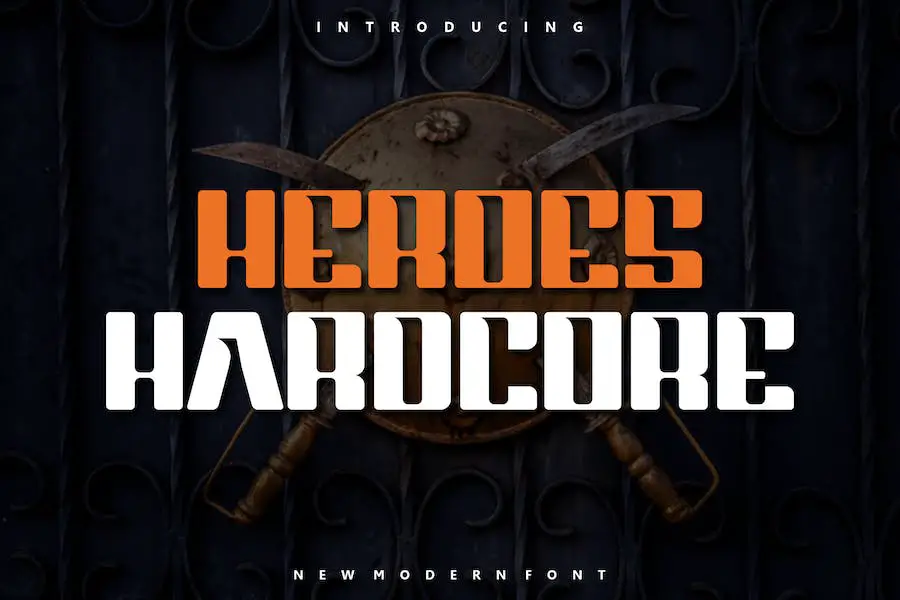
Heroes Hardcore adalah font luar biasa yang menghadirkan sentuhan berani dan autentik pada proyek desain Anda. Baik Anda sedang mengerjakan logo, pencetakan kaos, atau bahkan desain esport, font modern ini sangat cocok untuk menambahkan elemen yang kuat dan berdampak.
Dengan keserbagunaan dan gayanya yang unik, Heroes Hardcore menonjol dalam berbagai konteks dan akan meningkatkan keseluruhan tampilan dan nuansa kreasi Anda.
Kekuatan Heroes Hardcore terletak pada keberanian dan keasliannya. Font ini memancarkan kepercayaan diri dan memberikan kesan kuat dalam desain apa pun. Garis-garisnya yang bersih dan tepinya yang tajam memberikan tampilan yang modern dan ramping, dengan tetap mempertahankan sentuhan keunikan.
Saat digunakan dalam proyek branding, Heroes Hardcore menambahkan kepribadian dan karakter, membuat merek Anda menonjol dari pesaing.
Kasar
Hardcore adalah font unik yang menghadirkan sentuhan urban segar pada desain Anda. Skrip penuh gaya ini sempurna untuk menambahkan daya tarik yang menarik pada logo, citra merek, kutipan, kemasan produk, barang dagangan, dan postingan media sosial Anda.
Dengan estetikanya yang edgy dan modern, Hardcore adalah pilihan utama bagi para desainer yang ingin tampil berani. Baik Anda membuat logo untuk merek mutakhir atau mendesain grafis media sosial yang menarik perhatian, font ini siap membantu Anda.
Keserbagunaan dan nuansa trendinya menjadikannya suatu keharusan bagi setiap desainer yang ingin membawa proyek mereka ke tingkat berikutnya.
Distem
Distem adalah font logo hardcore yang menonjolkan gaya Horror Metal yang unik dan sangat detail. Sempurna untuk menambahkan sentuhan keren pada desain Anda, ini adalah pilihan yang sangat baik untuk desain retro-urban, branding untuk bisnis tato, logo, desain vintage, dan banyak lagi.
Estetikanya yang berbeda membedakannya dan menjadikannya font yang bagus untuk menciptakan visual yang menarik. Dengan tingkat detailnya yang mengesankan, Distem pasti akan memberikan kesan abadi dan menambahkan sentuhan kegelapan pada proyek Anda.
Baik Anda sedang mengerjakan logo, branding, atau proyek desain lainnya, font ini layak dipertimbangkan karena keserbagunaan dan dampaknya yang berani.
Hipster garis keras
Hardcore Hipsta adalah font tampilan vintage yang akan membawa proyek desain Anda ke level berikutnya. Dengan gaya reguler dan kasar, menghadirkan tampilan yang kuat, berani, dan tangguh pada karya Anda. Tampilannya yang percaya diri menjadikannya pilihan sempurna untuk menciptakan desain yang menarik.
Font ini memancarkan kesan kekuatan dan maskulinitas. Garis-garisnya yang bersih dan guratan yang berani memberikan kesan kuat pada halaman, sementara gaya vintage-nya menambahkan sentuhan nostalgia dan karakter.
Baik Anda mendesain poster, sampul album, atau kaos, Hardcore Hipsta akan menghadirkan tampilan yang edgy dan khas pada proyek Anda.
Gaya biasa dari Hardcore Hipsta menawarkan penampilan yang tajam dan halus, ideal untuk desain yang bersih dan modern. Di sisi lain, gaya kasar menambahkan efek berpasir dan tekstur, cocok untuk proyek yang membutuhkan estetika lebih usang dan vintage.
Penahan Berat
Heavy Stifle adalah font luar biasa yang akan menyempurnakan desain proyek grafis apa pun. Font unik ini, disebut Font Neraka Kuno – Font Modern, tebal dan autentik, menjadikannya sempurna untuk logo, templat, sampul album, produk, dan banyak lagi. Fleksibilitasnya memungkinkannya menonjol dalam berbagai situasi.